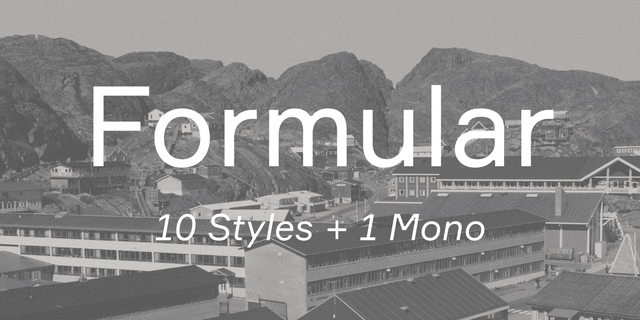
Formular — нео-гротеск в духе швейцарской школы нового поколения — не так догматичен, как его модернистские предшественники. Черты утилитарных старых гротесков 19-го века добавляют его характеру нотку эксцентричности. Дитя своего времени, он не стремится к идеальным формам, сохраняя при это универсальность и функционализм.
Шрифт спроектирован в пяти насыщенностях с наклонными начертаниями. Regular имеет моноширинную версию. Каждое начертание содержит альтернативный набор очень светлых знаков препинания, минускульные и табличные цифры, знаки препинания для прописных и стилистические альтернативы. Дизайнеры Вячеслав Кириленко и Гаянэ Багдасарян, 2014.
деловой, строгий, чистый, элементарный, ломаный, угловатый, минималистичный, самостоятельный, ответственный, западный, точный, ровный, убедительный, прямоугольный, стабильный, статичный, простой, нейтральный, современный, глобализированный, глобалистичный, монотонный, логичный, прагматичный, практичный, твердый, лаконичный, доступный, серьезный, устойчивый, автоматический, искусственный, холодный, инженерный, техногенный, стандартный, городской, резкий, четкий, острый, чертежный, компьютерный, урбанистичный, легкий, прохладный, тонкий, ясный, урбанистический, умный, железный, стальной, надежный, уверенный, машинный, индустриальный, военный, армейский, обязательный, важный, архитектурный, рабочий, сильный, суровый, жесткий, мотивирующий, железнодорожный, грубый, мощный, тяжелый, авторитетный, крутой, понятный, солидный, амбициозный, внушительный, мужественный, громкий, кондовый, политический, революционный, смелый, заметный, яркий, активный, броский, брутальный